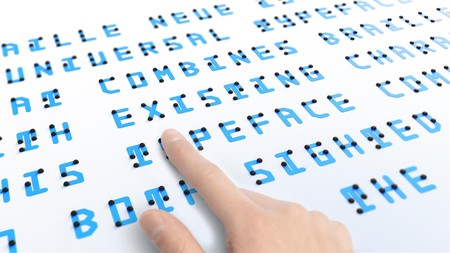
Para la gran mayoría de las personas que podemos ver, el braille es un lenguaje codificado imposible de entender. Es algo realmente impresionante, pero al mismo tiempo indescifrable.
Además, se necesita un espacio extra para colocar estos puntos en relieve, ya que no tienen la misma forma que las letras que utilizamos. El diseñador japonés Kosuke Takahashi se ha imaginado cómo sería una tipografía que combina estos dos mundos.
Una tipografía que se puede ver y tocar
Todo empezó cuando Takahashi decidió aprender braille, sorprendiéndose al darse cuenta que las formas no tenían nada que ver. Esto lo podemos ver, por ejemplo. en el número dos y el número tres (el 2 son dos puntos en vertical y el tres aparece representado con dos puntos horizontales).
Su investigación dio como resultado Braille Neue, una tipografía que pueden leer tanto personas invidentes como aquellas que pueden ver. Se puede leer con los ojos o con las manos, es una tipografía para todo el mundo.
Para conseguirlo, primero se fijó en la posición que tienen los puntos de braille y diseñó cada letra para que pase por esos puntos. En letras como la J, T , V o Z podemos comprobarlo.
Braille Neue presenta dos diseños diferentes: Standard (formando cada letra a partir de los puntos) y Outline (donde las letras están huecas y también se pueden escribir kanjis japoneses).
Su meta es implementar esta tipografía en los Juegos Paralímpicos de Tokio 2020. Este proyecto todavía está en fase de desarrollo, pero promete muchísimo. De esta manera el braille podría estar integrado en muchos más sitios y las personas que vemos podríamos acabar aprendiéndolo.